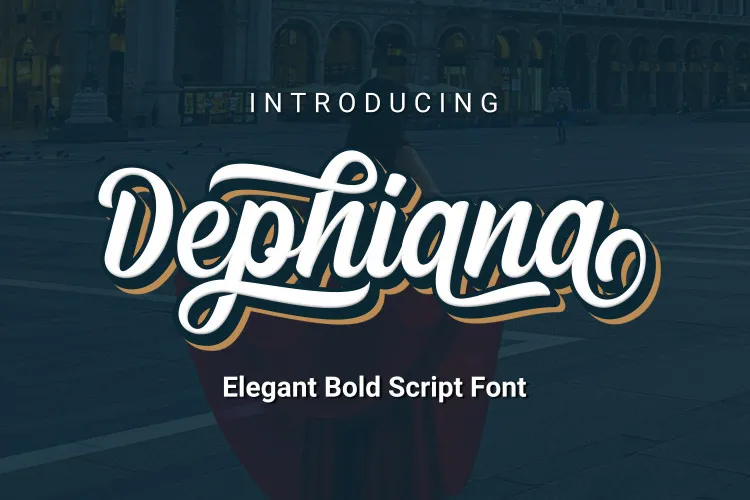
A Dephiana Bold Script Font é uma elegante solução para quem busca uma fonte script elegante e poderosa, perfeita para headlines, logotipos, etiquetas de roupas, convites, marcas, embalagens, anúncios e muito mais. Criada pelo designer NURF Designs, a Dephiana oferece alternativas estilizadas que permitem uma flexibilidade de uso, ideal para criar visuais incríveis em qualquer projeto. A fonte vem com todas as letras maiúsculas e minúsculas, sinais de pontuação, símbolos, números e setas alternadas estilo. Também é suportada por várias línguas, garantindo que a Dephiana atenda às necessidades de um público global. Perfeita para designers e criativos em busca de uma fonte versátil e poderosa, a Dephiana Bold Script Font está aqui para ajudar a dar vida ao seu próximo projeto. Em um mundo cada vez mais visual, é sempre bom contar com uma ferramenta que possa capturar sua paixão por design e transformá-la em algo que chamará atenção.